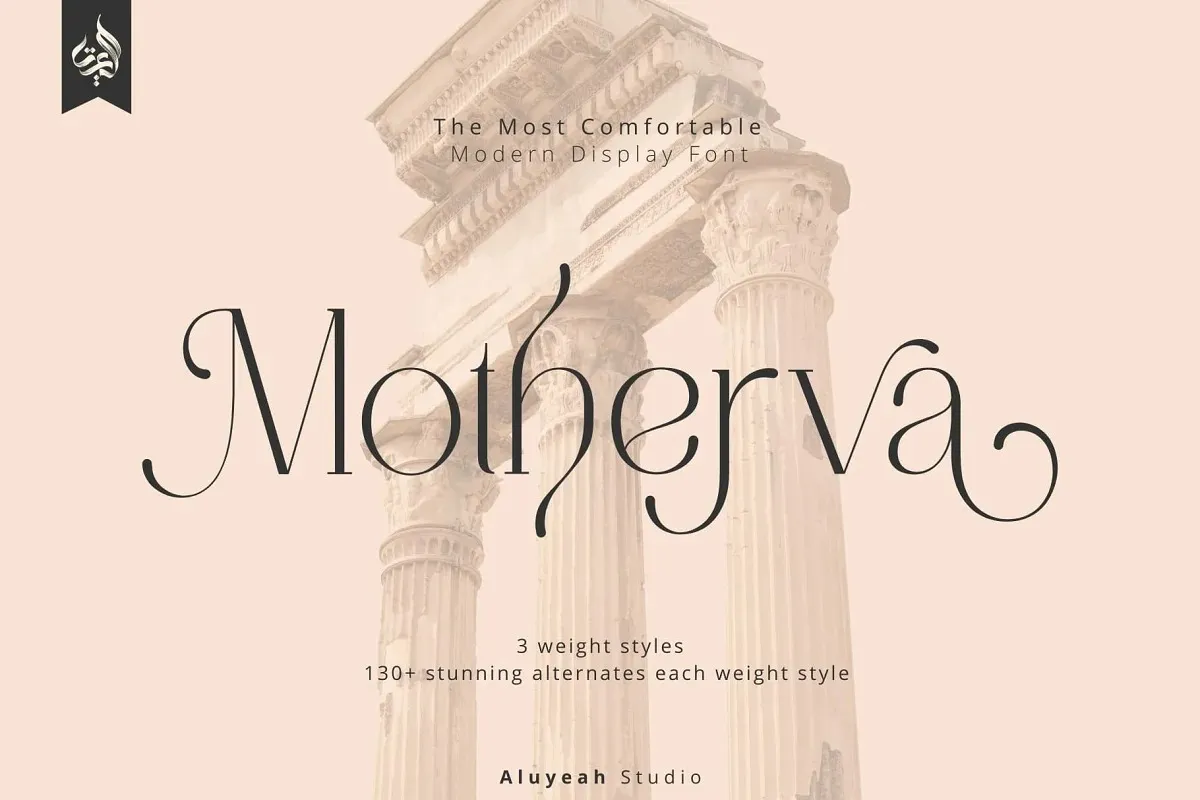
A Motherva Font é uma elegante tipografia serifada criada pela Aluyeah Studio, que incorpora formas clássicas com um estilo moderno. Este conjunto de fontes inclui três diferentes níveis de peso e traz mais de 130 alternativas incrivelmente atraentes e fáceis de usar para cada nível de peso. Perfeita tanto para textos formais quanto para design gráfico sofisticado, a Motherva é uma escolha inteligente para quem busca qualidade e facilidade em suas produções digitais. Seja para criar um design impecável ou apenas manusear texto com elegância, esta fonte representa o que há de melhor no mundo da tipografia serifada.